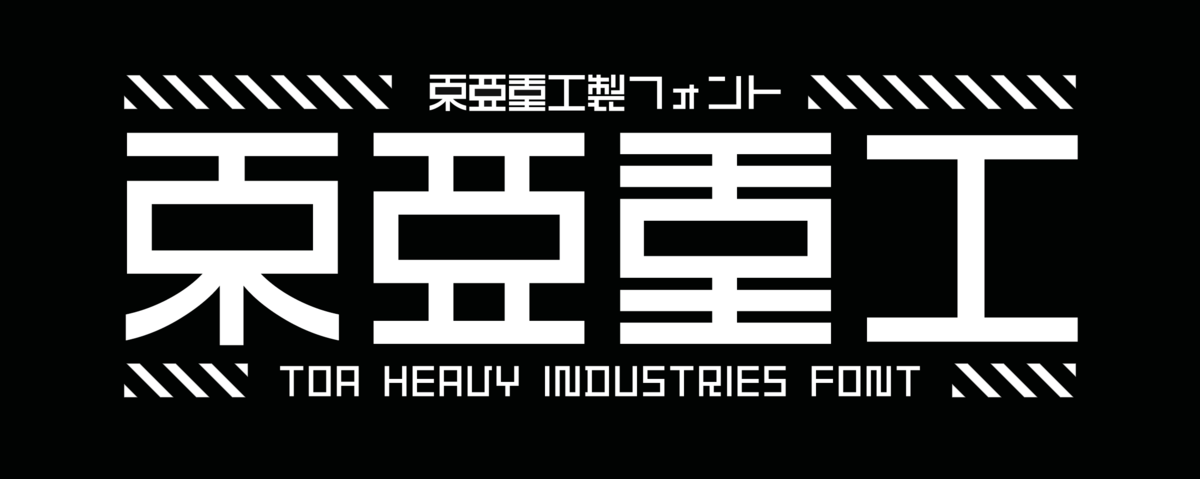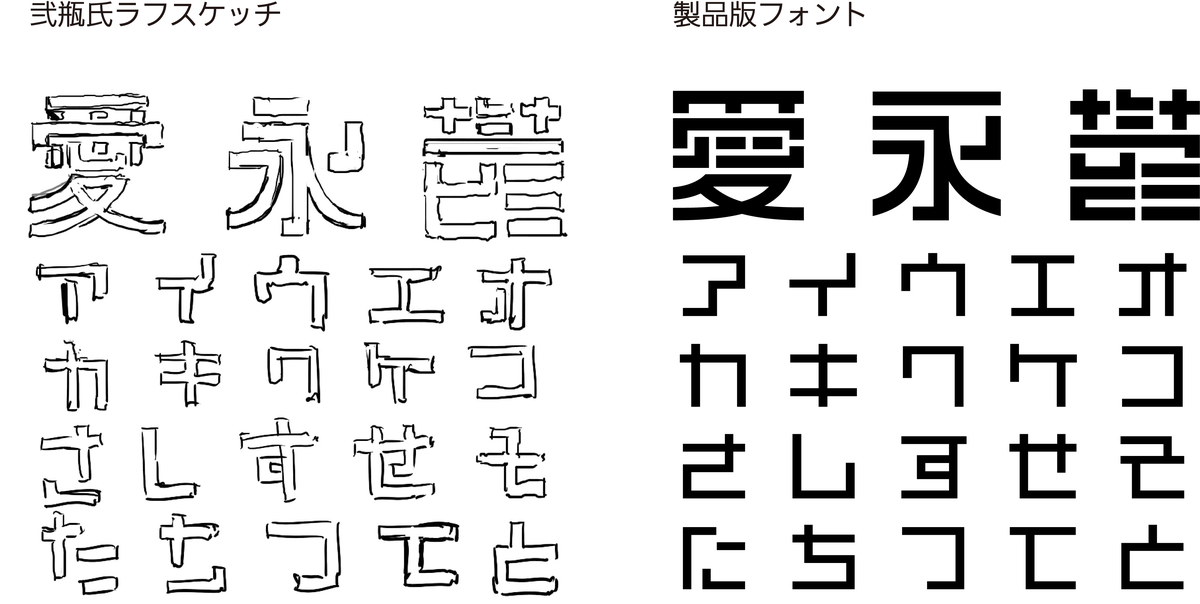
東亜重工製フォント「東亜重工」
イワタは、東亜重工有限責任事業組合(TOA Heavy Industries, LLP.、東京都港区)と共同で開発した東亜重工製フォント「東亜重工」を2020年12月15日(火)より発売したことを発表した。
東亜重工製フォント「東亜重工」は、漫画家の弐瓶勉氏(代表作:『人形の国』『シドニアの騎士』『BLAME!』など)の原案・監修のもと、同氏の多くの作品にも登場する文字をイワタが新たに開発・製造し、東亜重工製フォント「東亜重工」として製品化した。